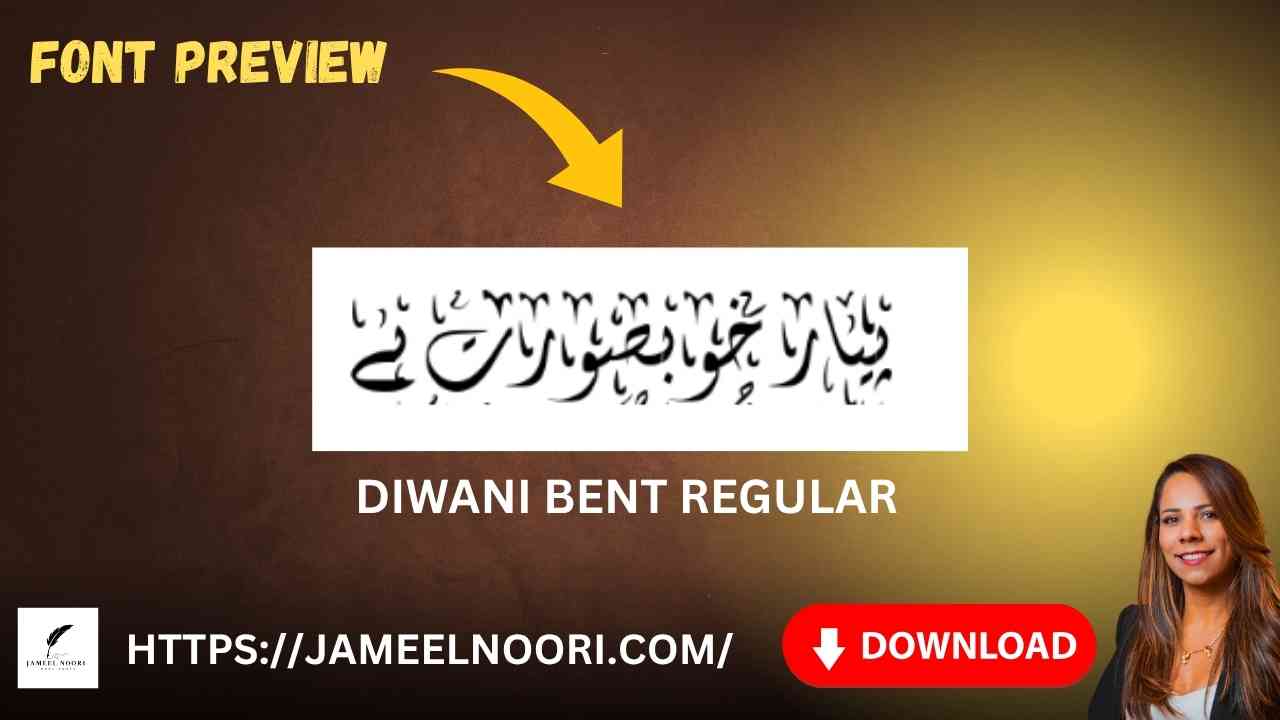
Agar aap Download Urdu font Diwani Bent Regular font dhoondh rahe hain to aap bilkul sahi jagah par hain. Ye ek stylish aur artistic Urdu font hai jo aksar calligraphy aur decorative text ke liye use hota hai. Is guide mein hum aapko batayenge ke is font ko kaise download karein, install karein, aur Urdu design projects mein use karein — woh bhi Roman Urdu mein, taa keh har koi asani se samajh sake.
What is Diwani Bent Regular Font?
Download Urdu font Diwani Bent Regular aik elegant aur Naskh-style inspired font hai jo Urdu aur Arabic calligraphy mein use hota hai. Ye font visually strong aur unique appearance rakhta hai.
• Stylish calligraphic design
StyleCalligraphic, Decorative
Where to Use Diwani Bent Regular Urdu Font?
Download Urdu font Diwani Bent Regular mostly design aur calligraphy projects mein use hota hai. Ye font special occasions, Islamic art, wedding cards aur posters mein elegant touch deta hai.
Common Use Cases:
• Urdu Poetry Posters
• Islamic Artworks
• Wedding Invitations
• Logo Design
Pakistan mein Urdu fonts ka craze din ba din barhta ja raha hai. Diwani Bent Regular font ki khubsurti aur readability usay aur fonts se alag banati hai.
• Easy to Read & Stylish
• Urdu aur Arabic dono scripts support karta hai
Agar aapko unique aur stylish Urdu font chahiye jo har design ko elegant look de, to Download Urdu font Diwani Bent Regular aap ke liye best choice hai. Iska artistic touch aur compatibility isay Pakistani designers ka favorite banata hai. Abhi download karein aur apne design projects ko next level par le jayein!